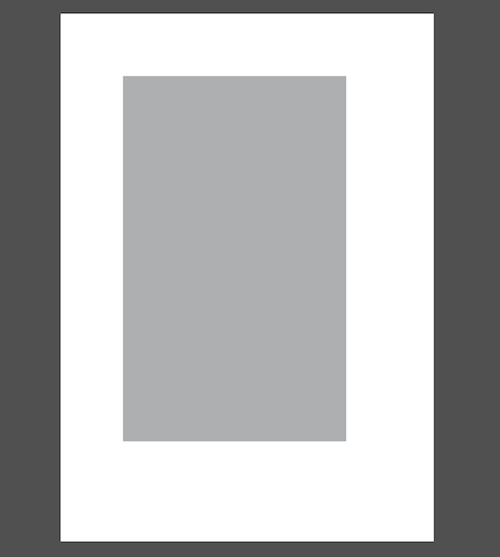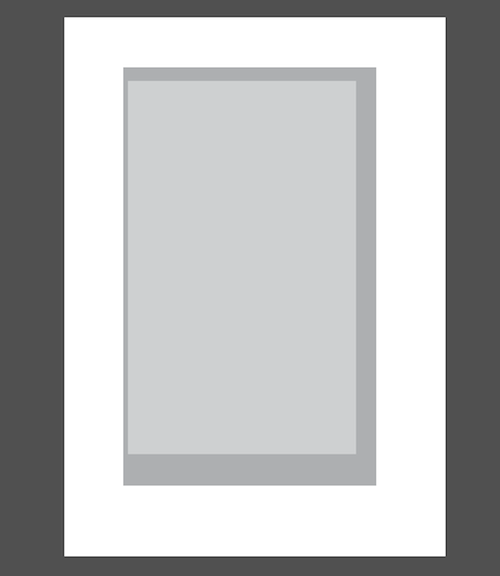
Cronos oder Myriad in Kombination mit Minion?
4,5 cm unten versuchen (wenn die Pagina unten sitzt)
Was heißt das genau? headinclude (global option) in LaTeX?
Innen könnte es mit 3 cm (je nach Bindung und Aufschlageverhalten) gut klappen, außen eventuell 3,5 cm.
Der Wert Innen (3 cm) ist für Doppelseiten zu verstehen, also für die linken Seiten rechts 1,5 cm Rand?
Hier ein konkreter Vorschlag, der sich schon in einigen (geisteswissenschaftlichen) Arbeiten bewährt hat: ein typischer Kompromiss, der nicht allzu weit vom gängigen Layout wissenschaftlicher Arbeiten entfernt ist (also nicht "zu gestaltet" aussieht), sich aber doch positiv abhebt:
Fließtext: Minion mit Schriftgröße 11,3pt und Zeilenabstand 16pt.
Ränder: oben 27mm (gemessen an der Grundlinie einer gedachten zusätzlichen Zeile oberhalb der ersten Zeile), unten 44,1mm (die krumme Zahl kommt zustande, da der Textblock ein Vielfaches des Zeilenabstands sein soll), innen 34mm, außen 40mm.
"Innen" und "außen" bedeutet: Rand, der auf einer Doppelseite jeweils innen bzw. außen liegt; auf einer rechten Seite beträgt der Rand also links 34mm und rechts 40mm, auf einer linken Seite entsprechend umgekehrt (der Wert gilt also pro Seite).
Wenn man an einer der typografischen Stellschrauben dreht, muss man die Auswirkungen auf die anderen Elemente beachten: 11,3pt Schriftgröße ist z.B. relativ groß; aber auch mit dieser Schriftgröße kommt man auf mindestens 80 Zeichen pro Zeile, was das obere Limit ist. Macht man die Schrift kleiner, erhöht sich die Zeichenzahl pro Zeile. Um die Lesbarkeit nicht zu beeinträchtigen, müsste man die Ränder vergrößern – und schon kann der Eindruck entstehen, als wolle man "Seiten schinden" durch große Seitenränder.
Bei der Erstellung des Satzspiegels ist auch zu beachten, welche anderen Elemente u.U. noch auf eine Zeile passen müssen: in Deinem Fall also möglicherweise Formeln, die nicht umbrochen werden sollen, oder Grafiken, die eine bestimmte Größe haben müssen, um noch gut erkennbar zu sein. ...
Zu den Überschriften: Ü1 könnte man deutlich größer machen als den Fließtext (und eventuell auch in einer Serifenlosen, wenn Du Dich nur ungern davon trennst) und ihr großen Raum auf der Seite geben (z.B. ein Drittel der Seite). Die restlichen Überschriften könnten in der Größe der Grundschrift bleiben und sich nur durch Abstand davor und danach abheben (diese Möglichkeit bietet sich an, da ja alle wichtigen Ü-Ebenen nummeriert sind). Für Ü2 also beispielsweise (wie es jetzt schon in Deinem Beispiel der Fall zu sein scheint) 2 Zeilen Abstand davor, eine Zeile danach, für Ü3 1 1/2 Zeilen davor, 1/2 Zeile danach, für Ü4 nur eine Zeile davor. Eine weitere Auszeichnung ist u.U. gar nicht nötig. Die Gestaltung der Überschriften hängt aber stark von der Struktur des Textes ab.
Und jetzt viel Spaß beim Ausprobieren! (Am besten mit "echtem" Text der eigenen Fachrichtung oder mindestens mit "sinnvollem" deutschen Text; die Wirkung von Fülltext in Pseudolatein ist u.U. ein ganz anderer als bei "echtem" Text.)
(...) die krumme Zahl [44,1 mm] kommt zustande, da der Textblock ein Vielfaches des Zeilenabstands sein soll (...)
Wie ist das gemeint?
Der Textblock berechnet sich in diesem Fall mit ohne Bindekorrektur/Beschnitt durch (297mm -44.1mm -27mm)⋅(210mm -40mm -34mm) = 307.224 cm^2
(297mm -44.1mm -27mm)⋅(210mm -40mm -34mm) = 307.224 cm^2
Ich glaube, so eine Berechnung hat hier noch niemand gemacht, um ein Layout zu finden … (Ich hatte mal einen Chef, der versucht hat, Textmengen über cm² zu brechnen – aber das ist eine andere, sehr lustige Geschichte).
Gemeint war sicherlich die 1 hinterm Komma, weil Schriftgröße und Zeilenabstand in Punkt keine "glatten" Millimeter ergeben.
Gemeint war sicherlich die 1 hinterm Komma, weil der Schriftgröße und Zeilenabstand in Punkt keine "glatten" Millimeter ergeben.
Verstehe!
Ich glaube, so eine Berechnung hat hier noch niemand gemacht, um ein Layout zu finden …
Aber zumindest den goldenen Schnitt (phi) könnte man zur Berechnung eines ästhetischen Textfeldes benutzen: Textblockbreite ⋅ φ = Textblockhöhe.:tutor:
Könnte man. Doch die Proportion des Papiers wird durch √2 bestimmt. Darin müsstest du jetzt den φ-Textblock harmonisch integrieren – das wird alles seeehr theoretisch, da würde ich mich lieber auf mein/dein Auge verlassen.
PS: Belletristische Buchseiten basieren mit durchschnittlich ca. 13 x 21 cm weitgehend auf dem Goldenen Schnitt.
– das wird alles seeehr theoretisch ...
Wenn ich es theoretisch angehe, dürfte ich – um im Durchschnitt nicht mehr als rund  72 Zeichen/Zeile zu haben – mit Minion bei 10.5 pt und einem Zeilenabstand von 1.3 Zeilen höchstens 108 mm Textbreite haben, was zu sehr großen Rändern führt (z. B. links 6 cm; rechts 4.8 cm).
Minion mit Schriftgröße 11,3pt und Zeilenabstand 16pt.
Darum ist dies ja auch ein bedenkenswerter Vorschlag.
Minion mit Schriftgröße 11,3pt und Zeilenabstand 16pt.